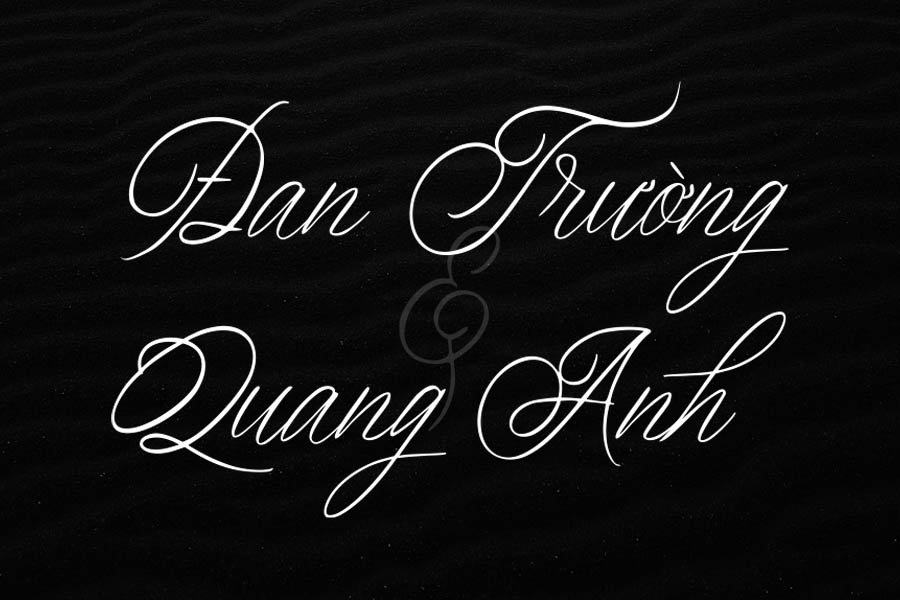
Phông chữ tiếng Việt chủ đề wedding viết tay TH Renddonika
TH Renddonika là một bộ font chữ viết tay mang phong cách thanh lịch, rất phù hợp cho những thiết kế cần sự mềm mại và tình cảm – đặc biệt là thiệp cưới, thiệp mời, thư tay hoặc các ấn phẩm mang hơi thở cá nhân. Ngay từ cái nhìn đầu tiên, font mang lại cảm giác như được viết bằng bút mực trên giấy, đầy tự nhiên, nhẹ nhàng và gần gũi.
Điểm ấn tượng ở Renddonika là nét chữ uyển chuyển nhưng không quá cầu kỳ, vừa đủ để tạo điểm nhấn mà vẫn dễ đọc. Các ký tự thường được nối liền nhau một cách mượt mà, tạo nên sự liền mạch và nhẹ nhàng trong tổng thể văn bản. Trong khi đó, các chữ cái hoa lại có chút bay bổng, với những nét lượn đẹp mắt – rất lý tưởng cho việc đặt tên cô dâu chú rể trên thiệp cưới hay bìa album ảnh.
Font đặc biệt phù hợp với những thiết kế có chiều sâu cảm xúc: từ thiệp mời cưới, bao thư, tiêu đề thư tay cho đến các thiết kế mang phong cách thủ công như nhật ký, thư tình, trích dẫn trang trí hay bài đăng Instagram nhẹ nhàng. Bạn cũng có thể dùng font này trên các chất liệu như giấy kraft, giấy mỹ thuật, nền pastel hoặc các bảng màu vintage – nơi mà sự tinh tế luôn được ưu tiên hàng đầu.
Về mặt kỹ thuật, TH Renddonika đã được Việt hóa hoàn chỉnh bởi đội ngũ S99.VN, đảm bảo hỗ trợ đầy đủ các dấu tiếng Việt như sắc, huyền, hỏi, ngã, nặng… Từng dấu thanh được căn chỉnh hài hòa với nét chữ, giúp bạn sử dụng mượt mà mà không cần chỉnh sửa thủ công, ngay cả với văn bản dài hoặc thiết kế in ấn chuyên nghiệp.
Không chỉ là một font đẹp, TH Renddonika còn là lựa chọn lý tưởng để truyền tải cảm xúc một cách tinh tế và gần gũi. Dù bạn là designer chuyên nghiệp hay người làm thiệp thủ công tại nhà, đây là font không thể thiếu trong bộ sưu tập chữ viết tay dành cho các thiết kế mang tính cá nhân.
TH Renddonika được Việt hóa bởi đội ngũ S99.VN, với hệ dấu được xử lý trọn vẹn – sắc, huyền, hỏi, ngã, nặng đều được đặt đúng tỷ lệ và vị trí, giúp font dễ sử dụng trên mọi nền tảng mà không cần chỉnh sửa thủ công.